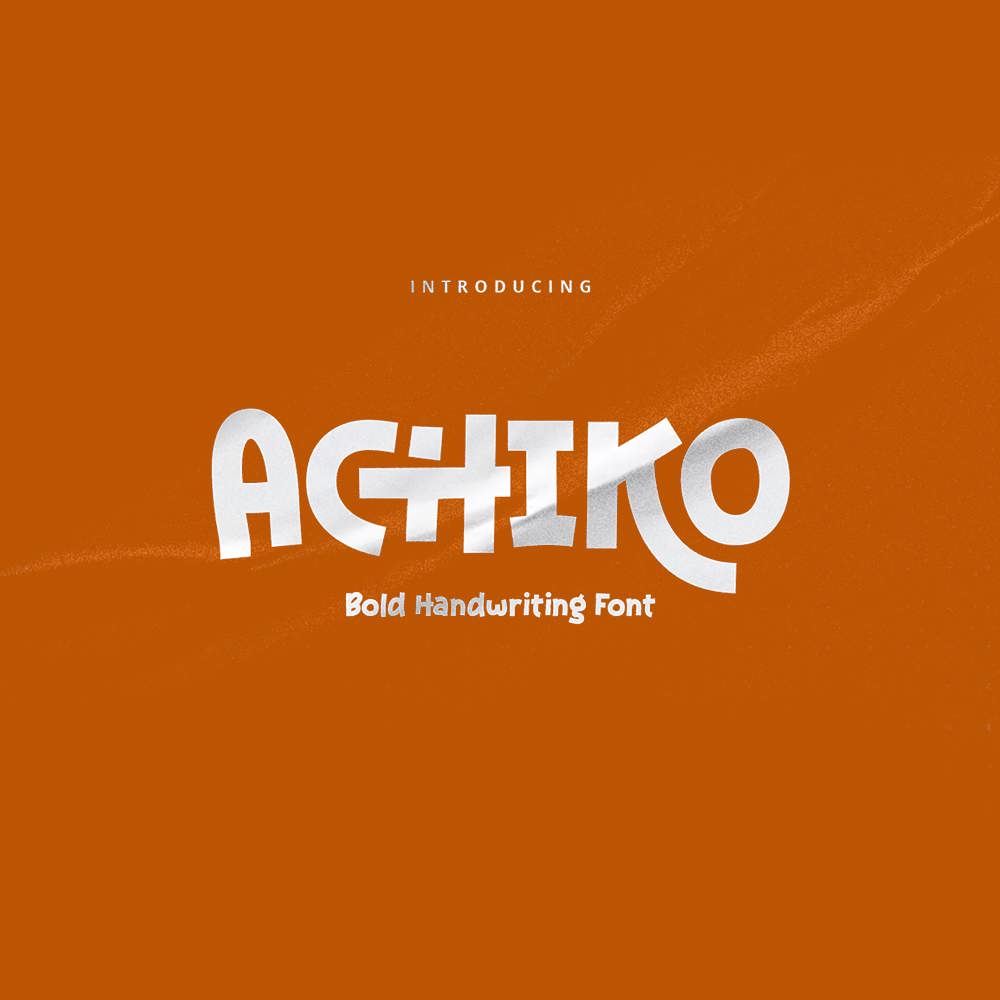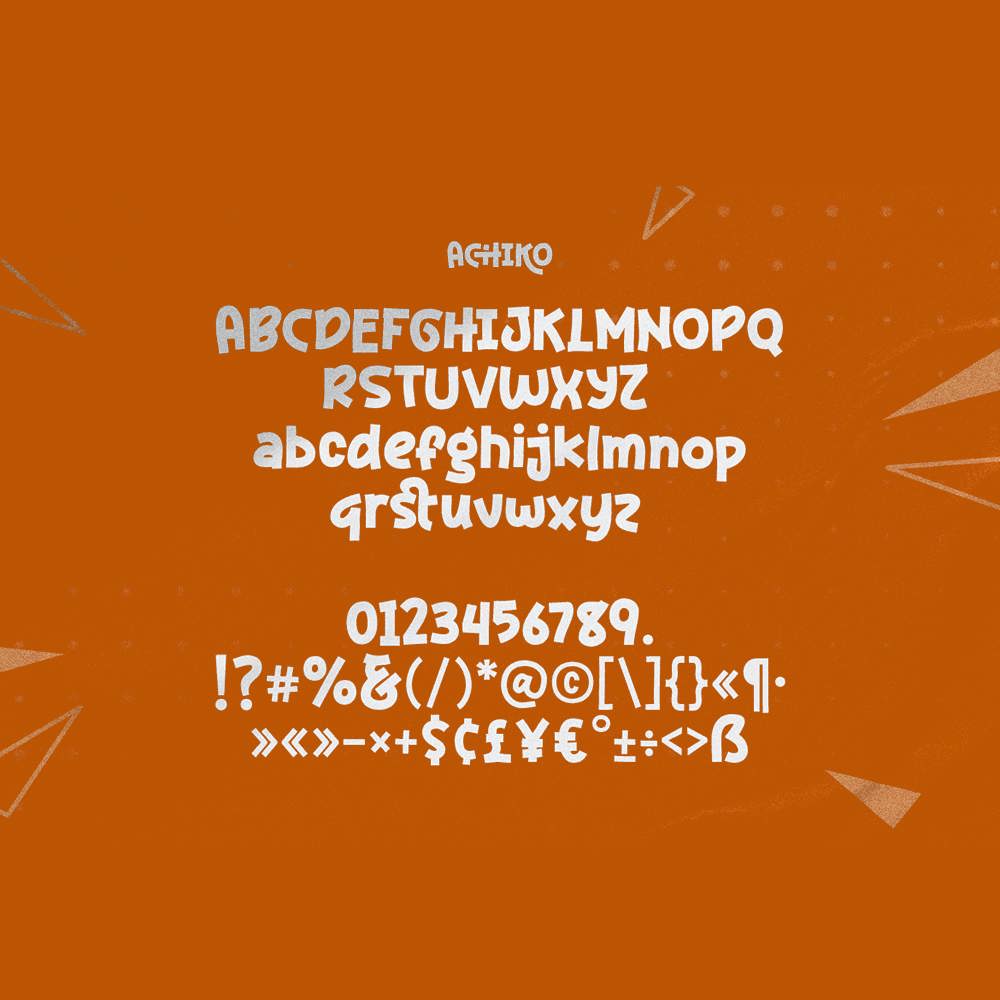
فونت پرمیوم و انگلیسی Achiko Font یک فونت خوشنویسی جسورانه است که به خاطر لبههای تیزش متمایز میکند. این فونت جریان پویای خوشنویسی طبیعی را با حضوری قوی و قاطع ترکیب میکند. لبههای تیز به آن جلوهای مدرن و جسورانه میبخشد و آن را برای تیترها، لوگوها و موارد تبلیغاتی ایدهآل میکند. Achiko که به لیگاتورهای منحصر به فردی مجهز است، ارتباطات روان و بصری جذابی را بین حروف تضمین میکند و لایهای اضافی از پیچیدگی و خلاقیت را به متن شما اضافه میکند. چه روی طرحهای دیجیتال کار کنید و چه روی پروژههای چاپی، Achiko جلوهای جسورانه و زیبا به کار شما میبخشد.
مزایای استفاده از فونت لاتین Achiko چیست؟